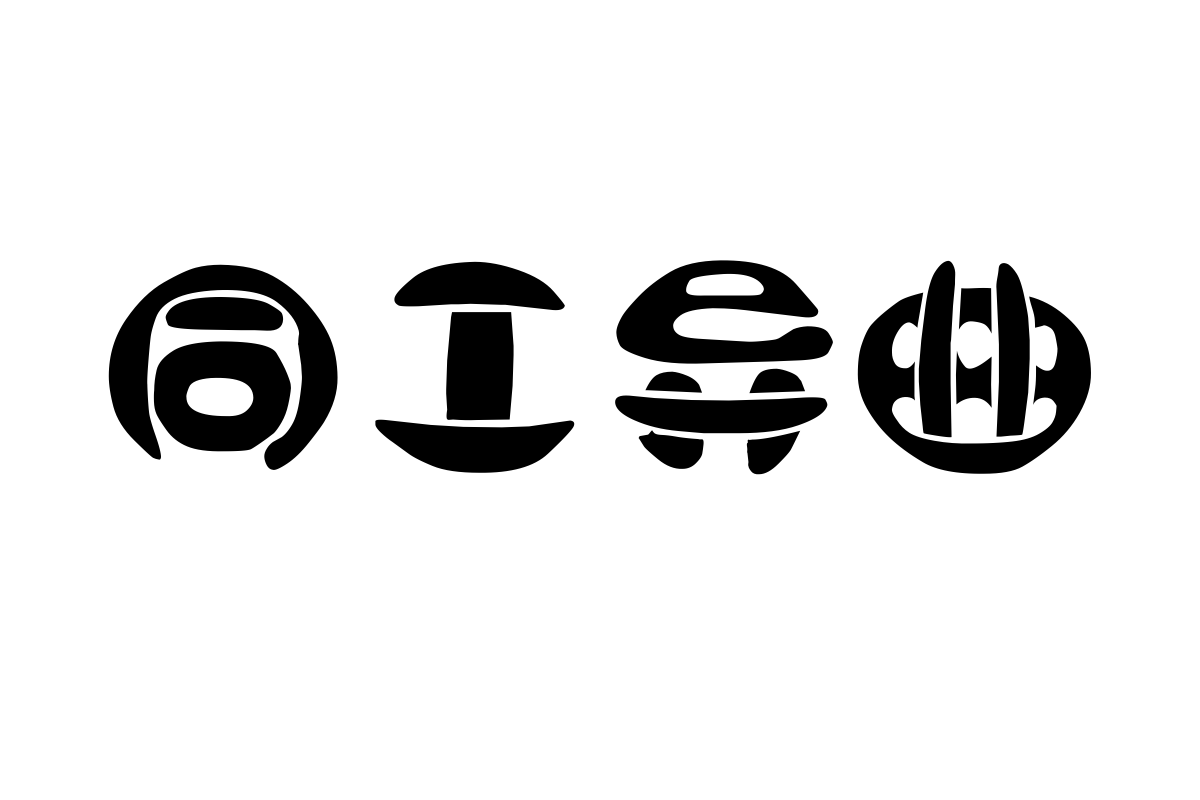
汉仪黑棋体简是一款具有现代感的中文字体,它以简洁、大方的风格为特点。这款字体采用了较为粗犷的笔画线条,使得整体呈现出一种强烈的视觉冲击力。同时,它的字形结构也相对规整,易于阅读和识别。
在设计上,汉仪黑棋体简注重细节的处理,无论是字母还是数字,都保持了一定的一致性和协调性。这使得它在各种场合下都能展现出良好的视觉效果。
总的来说,汉仪黑棋体简是一款适合用于广告、宣传、标题等需要突出显示文字的场合的字体。它以其独特的风格和易读性,赢得了广泛的赞誉和喜爱。